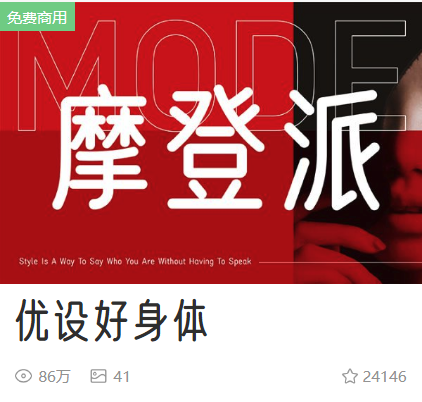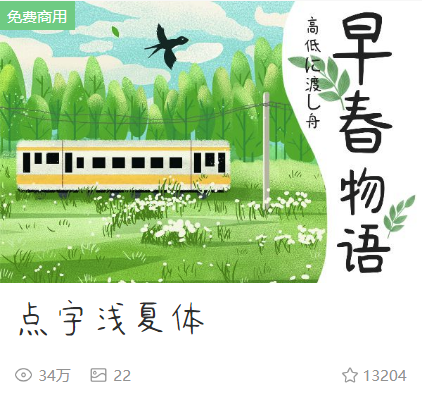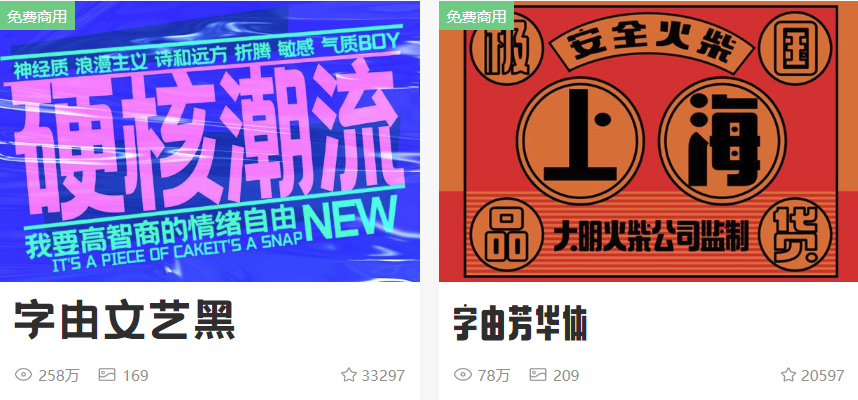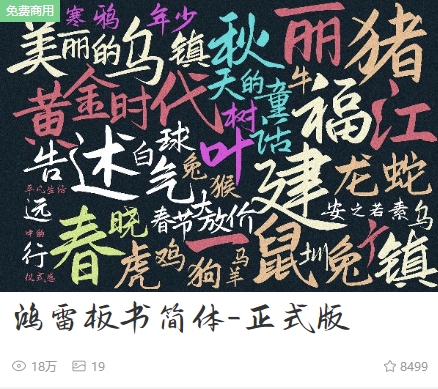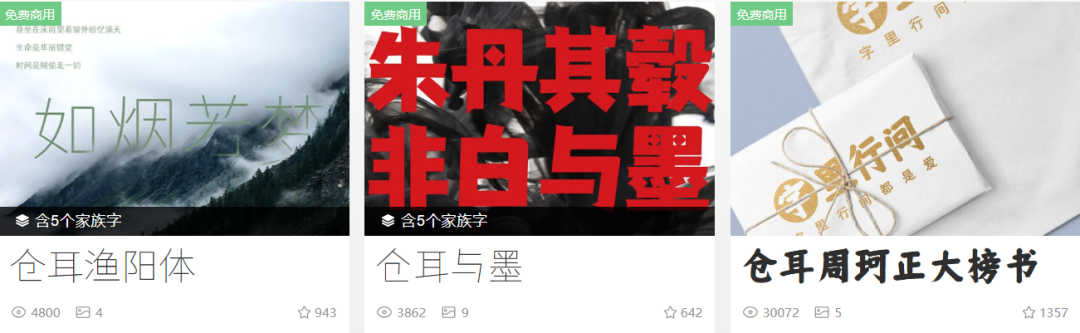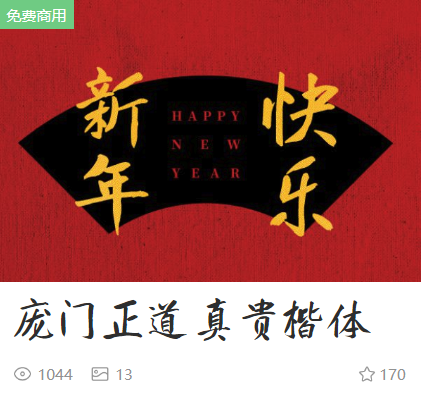
眼看着这一年就要在寒潮中抖完了,再不发点福利,搞点事情,就来不及了,所以柚子临时起意,要给你们送点温暖~
这一年应该是免费字年,光字由就发了两款CP字。
还有跟优设联合发布的优设好身体,补偿的点字浅夏体。
不过这还不够,演示系列(keynote研究所)那才叫一个井喷式发字,一年贡献了五款!
仓耳字库也发了很多,还都是家族(发现没,字由把家族字都折叠了,不再一款款展示了)。
至于其它字库品牌,也陆陆续续发布了不少……
有人说,就这?nonono,当然还有其它免费字,只是在去年或更早之前发布的,柚子就不一一举栗了,你可以在客户端里跟它们偶遇~
不过这里要特别提到免费英文,因为中文的免费字获取的渠道比较多,而英文就不一定了,有的要翻墙,有的不确定版权。
Don't worry,下载一个字由客户端就搞定了,这一年字由整理收集了上百款免费的英文字,有手写的、特效的、涂鸦的、图形的……
有了它们,天天给订阅号封面换字,也毫无压力了。